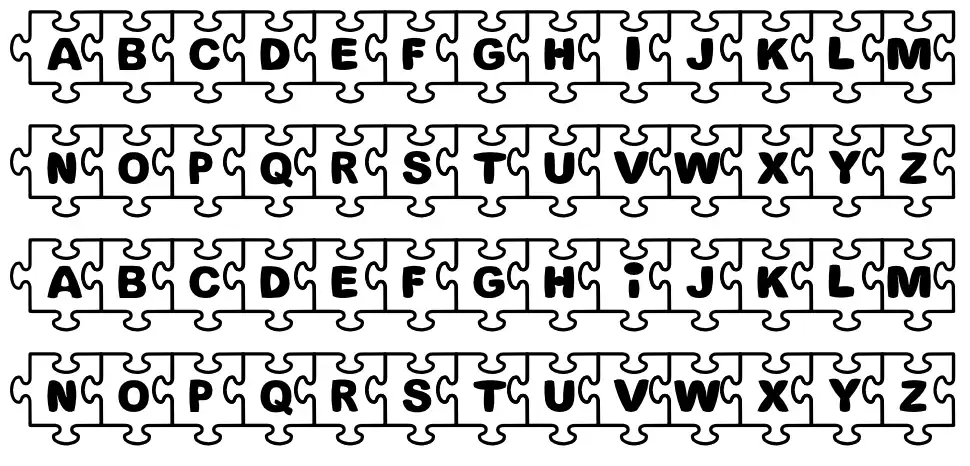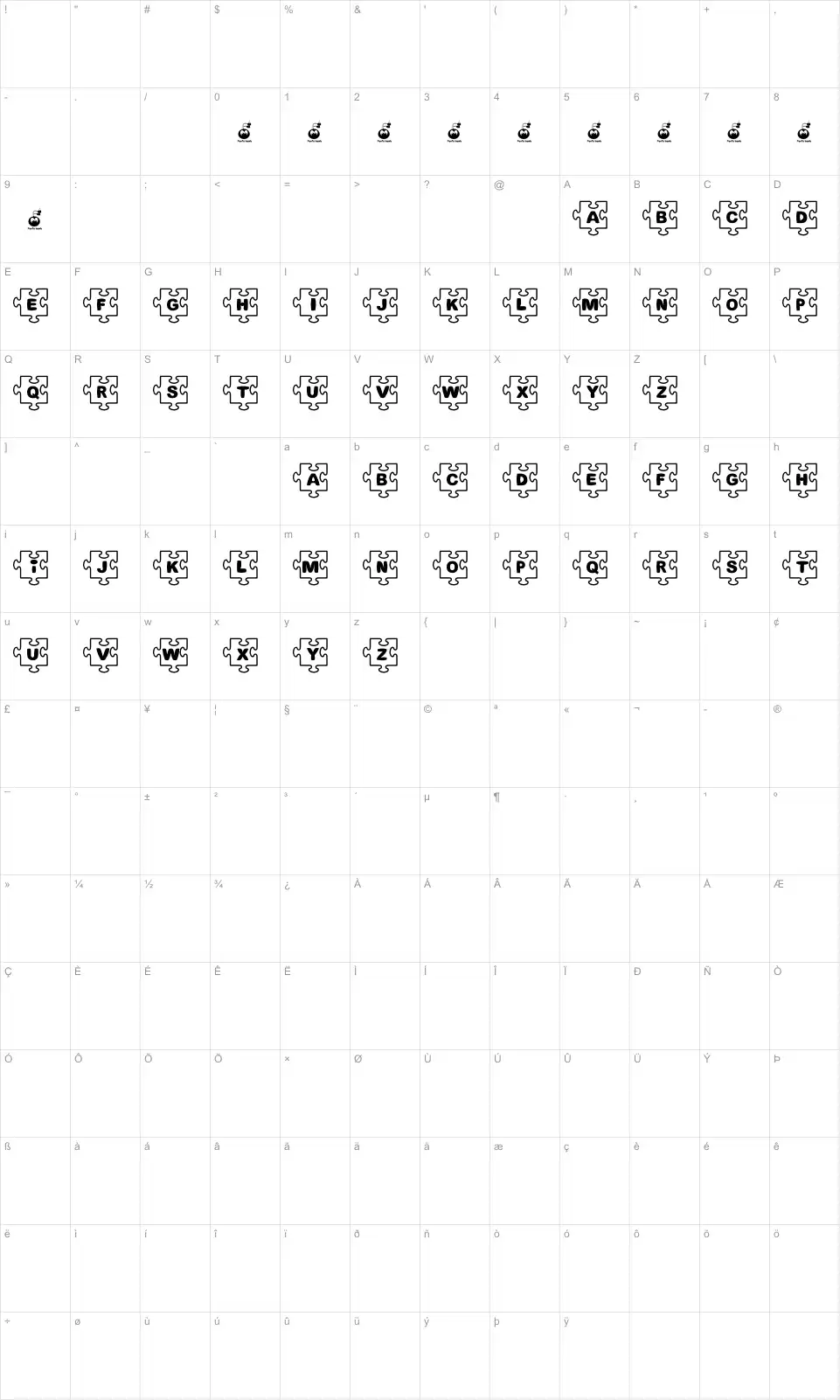
A fonte Fonts Bomb Jigsaw, da categoria Fancy e Decorative, é uma criação da Fonts Bomb que oferece uma aparência chamativa e desenhada com muita delicadeza. Esta fonte está disponível gratuitamente em formato TTF, permitindo que designers e criativos a usem em seus trabalhos sem custos adicionais. Com um design elegante e sofisticado, esta fonte é adequada para criações de design personalizadas e gráficos extravagantes. Foi adicionada à biblioteca de fontes em 12 de julho de 2022, e já foram instaladas em mais de 2648 sistemas diferentes, o que demonstra sua popularidade e qualidade. Com tamanho de arquivo compacto de 9 KB, Fonts Bomb Jigsaw é uma opção ideal para designers que buscam uma fonte divertida e versátil para projetos de design. Descarregue a fonte ou gerar um preview de texto personalizado online para ver como ela se assemelha antes de integrá-la em seus trabalhos.
Categoria: Fancy › Decorative